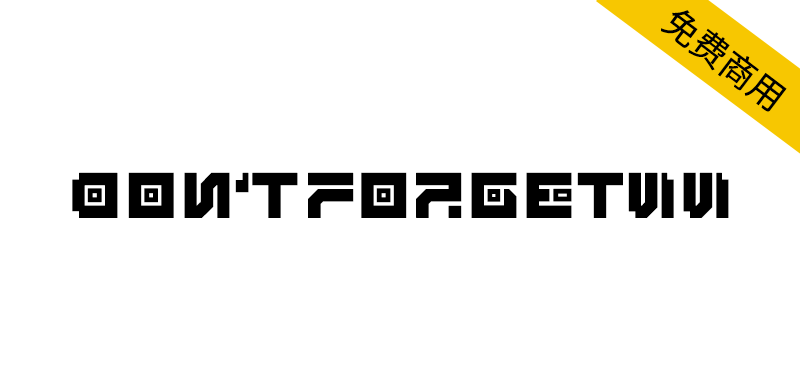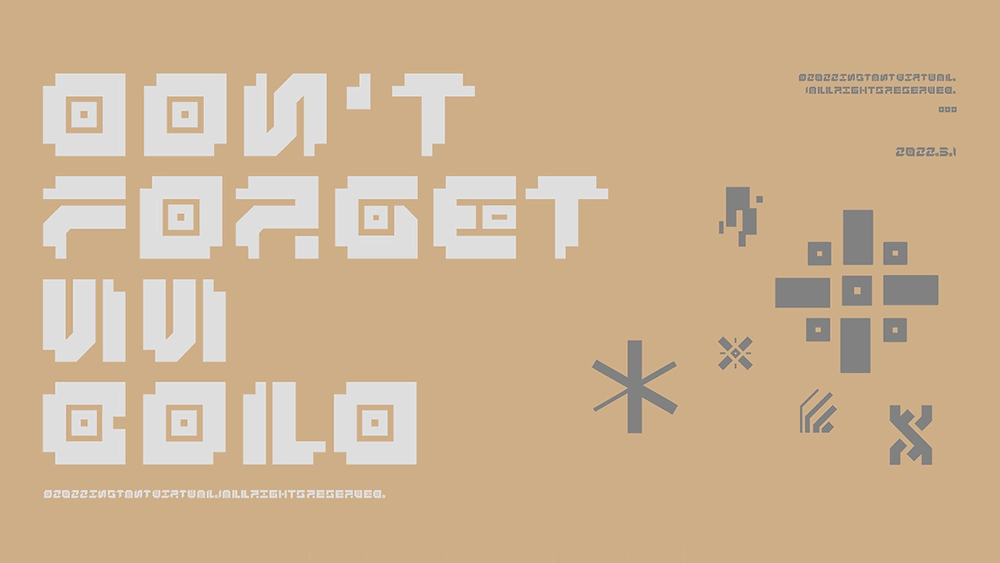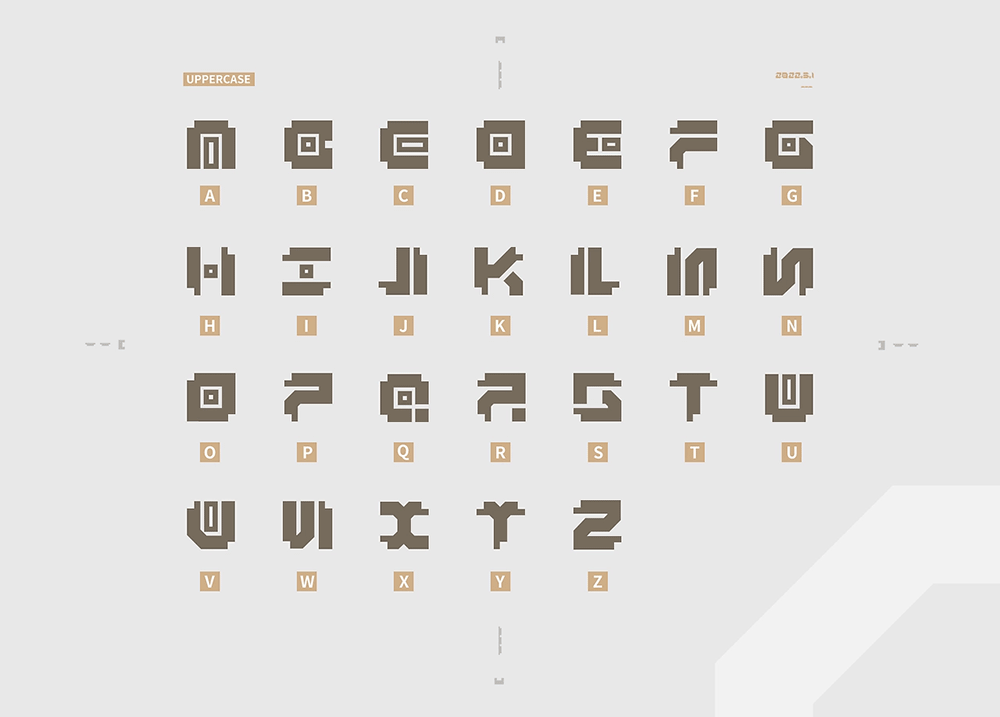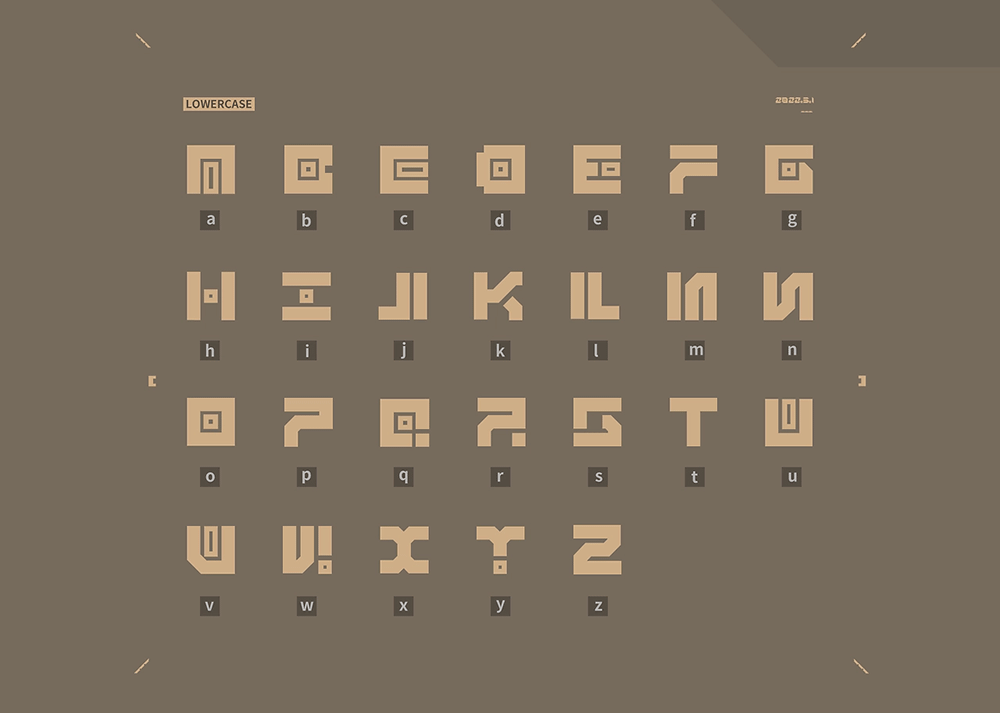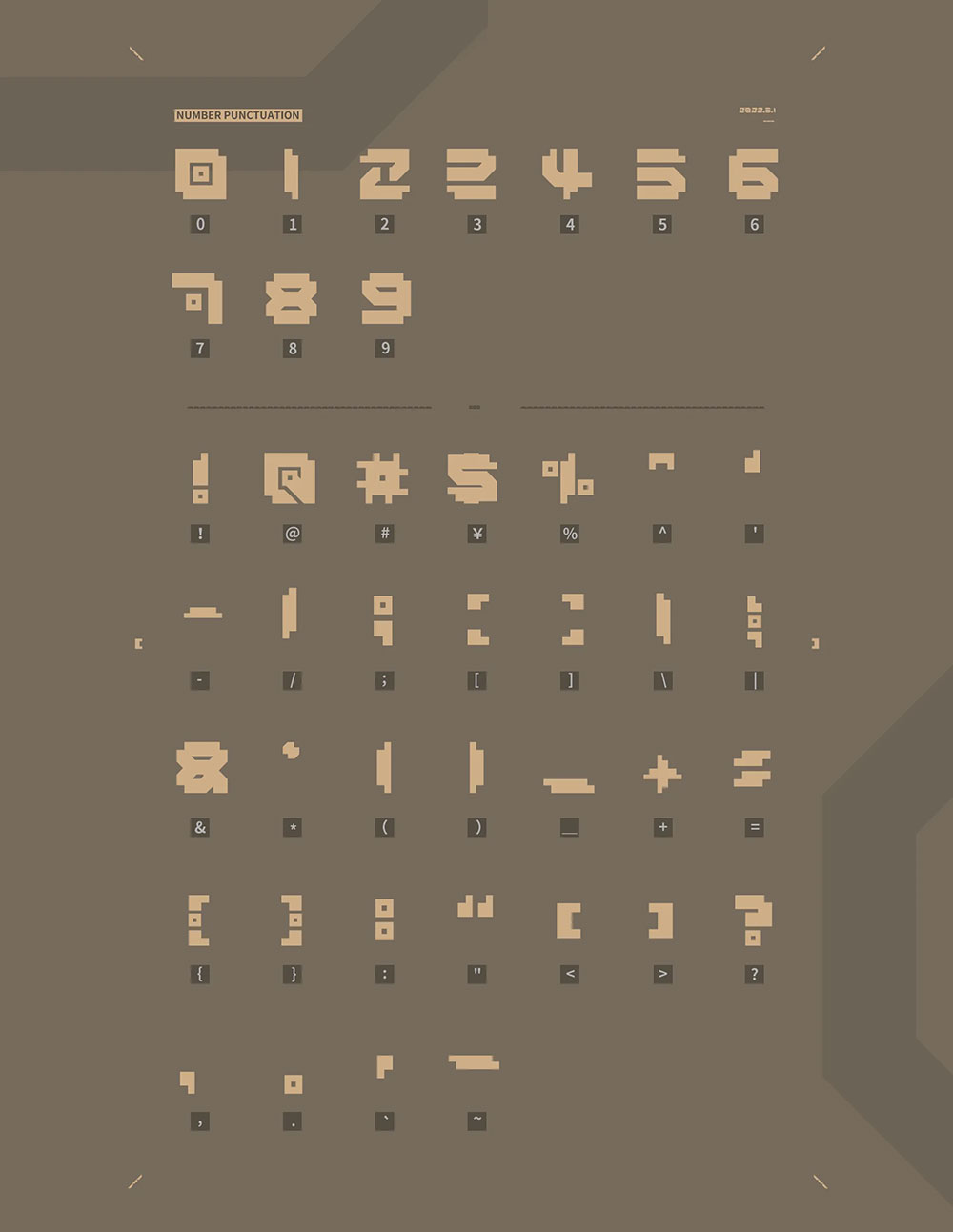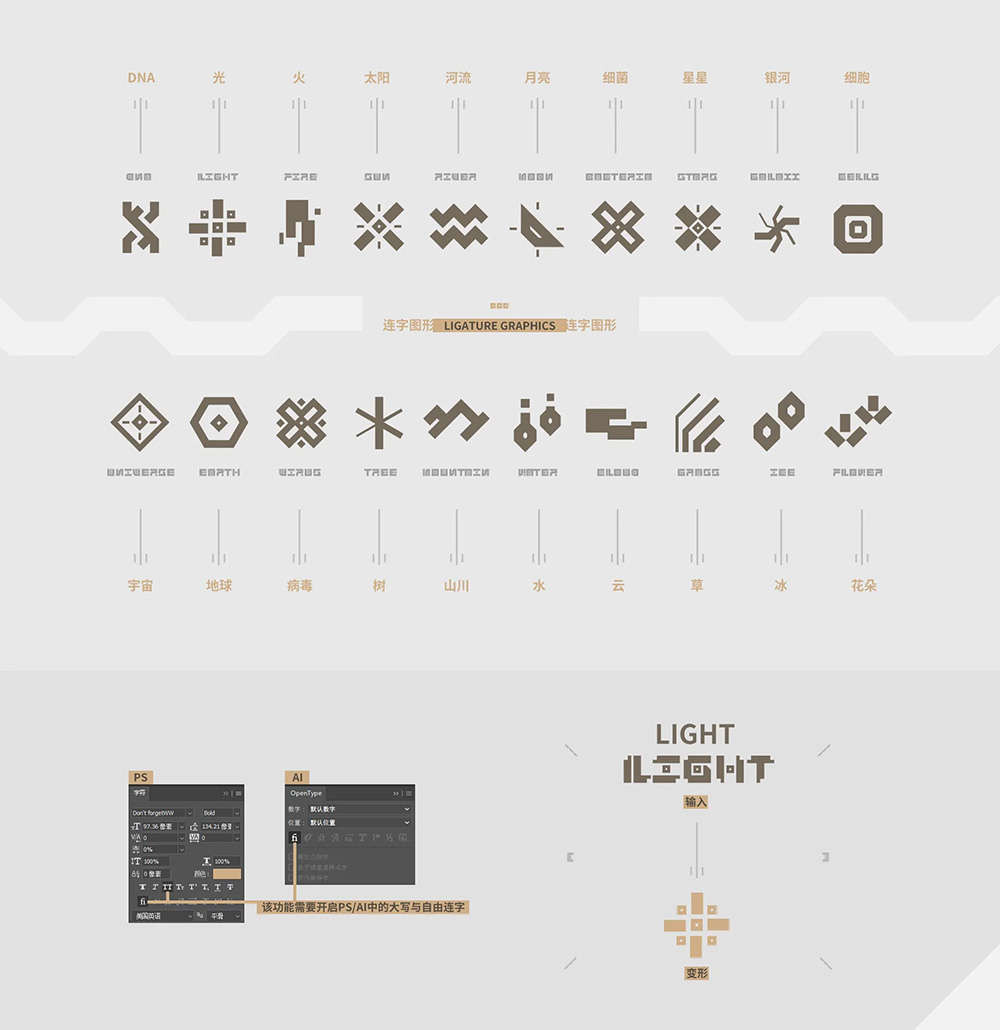
勿忘黑体(Don't forgetWW)是我以普玛彭古和一些古文明为灵感创作的一款基于英语的装饰性字体,你可以通过修改字体的间距,改变字与字的连接以达到传达不同感受的目的;还可以将残缺部分拼接成新的图形,字体还包含连字图形和部分符号,小写字体会减少部分细节。
勿忘黑体是一款装饰性字体,不推荐使用在正文排版设计当中。推荐使用场景:风格化标题、点线面装饰。
自从人类文明出现以来,人们一直都在思考如何传达思想与记录,古文明中人们用石头创作艺术和文学,推动了社会的发展。因为石头的特性能保存非常久的时间,后人也能了解学习前人的发展历史。
勿忘黑体是一款结合了古文明遗址、壁画、文字艺术的具有复古与未来感的实验字体。该字体的字面非常大,我舍弃了部分辨识度让它看起来像是某种符号,正方形的字形传达出一种神秘的无机感。勿忘黑非常适合用于创作具有未来、神秘感的视觉作品当中。
我把大自然界中的部分元素以几何图形的形式表现出来,我想传达一种从具象到抽象有机到无机的转换中形成的“距离感”。你可以通过调整字体间距连接字与字组成新的形状感受,另外还可以将文字残缺部分拼接成新的图形,适合用于装饰画面。
之所以我把这款字体命名为“勿忘黑体”,是因为想通过这款字体传达出在当今快节奏的信息时代当中,人们失去了自我判定能力,迷失了自我的发展方向。古文明中文字的发明是人类社会发展非常重要的标志之一,也提高了人类的思维能力,我希望人们不要“忘记”人类天生的求知欲望。“勿忘”象征了满足了物质需求的同时本能的去探索挖掘事物本质以及达到更高精神追求。
勿忘黑体包含大写字母26个、小写字母26个、符号+标点共32个、连字图形20个。使用连字图形时需要开启PS/AI中的大写与自由连字功能